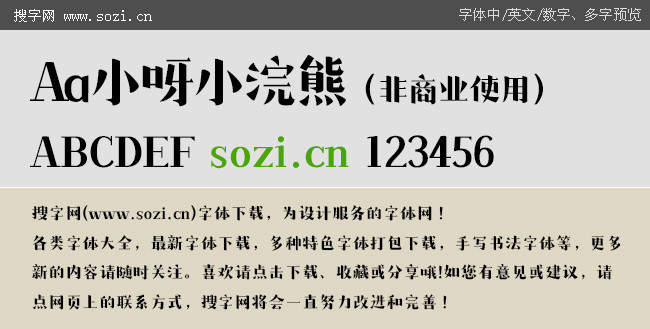
Aa小呀小浣熊
搜字網(wǎng)給大家提供一款A(yù)a小呀小浣熊(非商業(yè)使用)中文字體下載,該字體是一款個性的藝術(shù)字體,字體由宋體字進(jìn)行變化,筆畫趣味性十足。具有很好的視覺感,適用于平面宣傳設(shè)計(jì)、網(wǎng)頁設(shè)計(jì)、海報(bào)設(shè)計(jì)等應(yīng)用(此字體為個人非商用版,商用可以聯(lián)系QQ:1006760504)。